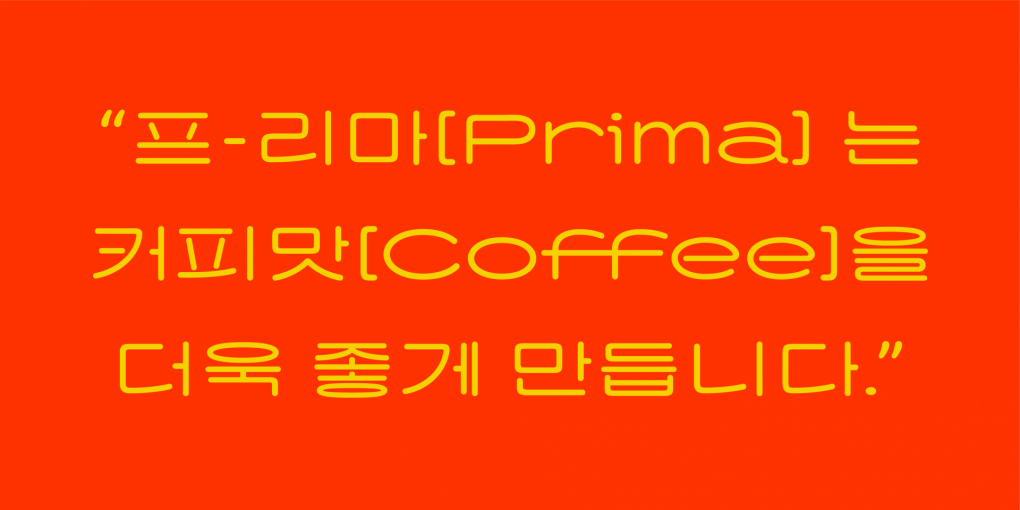
이상한 나라의 「SD 커오히」
새로우나 이상한 것과 마주칠 때의 마음
어떤 폰트나 레터링을 처음 봤을 때, 그 순간에는 정말 이상하다고 생각했더라도 시간이 흐른 후에 해당 폰트나 레터링이 새롭고 매력적으로 다가왔던 경험이 있으신가요? 생전 처음 보는 스타일의 창작물을 볼 때 이런 일이 잦았던 것 같아요. 저에겐 이 프로젝트를 진행하며 접했던 이전 시대의 레터링이 그러했습니다.
레트로와 「SD 커오히」의 관계
아르누보, 퓨처리즘, 사이키델릭, Y2k 등 한 시대를 풍미한 다양한 스타일을 아시나요? 「커오히」도 이러한 작업의 유용한 재료가 되고 싶었어요. 「커오히」라는 이름도 레트로 광고의 나레이션에서 영감을 얻었어요. 전체적으로 카피를 아련하고 느리게 끌며 말하는 것이 그 시대의 특징처럼 느껴졌거든요. ‘커피’를 천천히 늘여 부른 걸 소리 그대로 적었어요. 폰트 너비가 가로로 긴- 평체라는 점에서도 잘 어울립니다. 또 제작하며 커피를 좀 많이 마신 것도 그 이유가 되었을지도요.☕ 「커오히」가 선택한 시대는 1950~1960년대 입니다. 「커오히」는 그 시대에 그려진 레터링 원도를 재해석해 만들어졌어요.
복원과 재해석
「커오히」는 획 끝과 모서리를 둥글게 굴린 라운드 스타일의 폰트입니다. 특히 글자의 모서리 부분 안·밖의 선 모두에 곡률을 적용했어요. 커오히와 같은 ‘라운드’스타일의 폰트인 「Sandoll 고고라운드Cond」를 보세요. 모서리 부분 바깥 획만 둥글고 안쪽은 직선입니다. 글자 내 생기는 좁고 복잡한 공간을 깔끔하게 보여줘요.
하지만 「커오히」는 안과 밖 모두에 라운드 처리를 했습니다. ‘빵’ 쌍비읍의 아주 작은 모서리에도 예외 없이요. 글자 내 곡선이 늘어날수록 판면에서 「커오히」의 부드럽고 친근한 인상이 강조돼 보였어요. 크게 휘어지는 곡선이 오래된 세탁소 창문에 붙은 시트지와 빵집 간판의 글자를 떠올리게 하지 않나요?